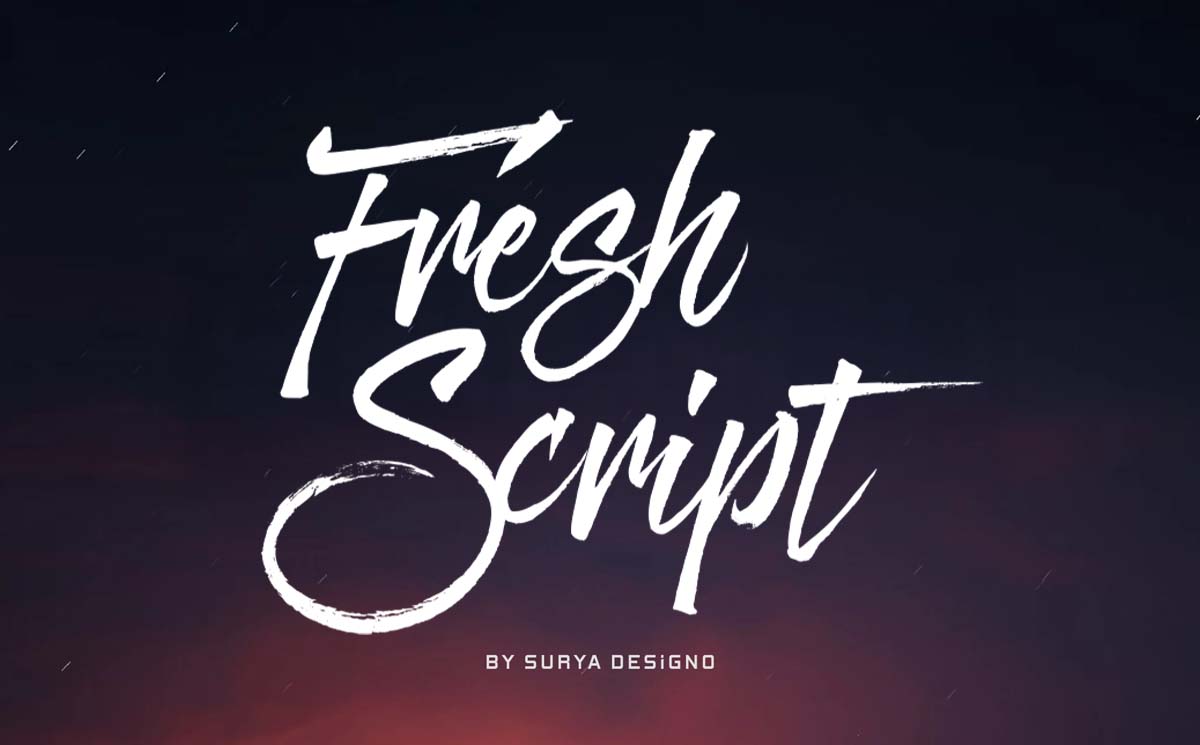
Font chữ tiếng Việt brush miễn phí cho chủ đề halloween SVN Fresh Script
SVN Fresh Script là font chữ tiếng Việt brush miễn phí sở hữu những đường nét phóng khoáng, tự nhiên và giàu cảm xúc, đặc biệt phù hợp với các thiết kế mang chủ đề Halloween. Với phong cách chữ viết tay mạnh mẽ, có chút ma mị nhưng vẫn dễ đọc, font giúp tiêu đề, poster, banner và ấn phẩm truyền thông trở nên nổi bật hơn mà không cần xử lý typography quá phức tạp.
Nếu bạn đang tìm kiếm một font brush Việt hóa để sáng tạo thiệp mời lễ hội, bài đăng mạng xã hội, hình ảnh quảng cáo hoặc nội dung trang trí Halloween, SVN Fresh Script là lựa chọn đáng cân nhắc. Bộ font mang đến cảm giác thủ công độc đáo, hỗ trợ trình bày nội dung tiếng Việt thuận tiện và có thể ứng dụng linh hoạt cho nhiều phong cách thiết kế khác nhau.
Font chữ tiếng Việt brush miễn phí cho chủ đề Halloween SVN Fresh Script đầy cá tính và ma mị
Font chữ tiếng Việt brush miễn phí cho chủ đề Halloween SVN Fresh Script gây ấn tượng nhờ kiểu dáng mô phỏng những nét cọ được viết nhanh bằng tay. Các ký tự có độ nghiêng và sự chuyển động rõ rệt, tạo cảm giác như từng con chữ vừa được vẽ trực tiếp trên bề mặt thiết kế. Đặc điểm này giúp font phù hợp với không khí sôi động, bí ẩn và có phần tinh nghịch của mùa lễ hội Halloween.
Không chỉ dành riêng cho những thiết kế kinh dị, SVN Fresh Script còn có thể được sử dụng trong nhiều dự án cần sự trẻ trung, tự do hoặc giàu năng lượng. Nhà thiết kế có thể kết hợp font với các gam màu cam, đen, đỏ sẫm, xanh rêu hoặc trắng ngà để xây dựng nhiều sắc thái khác nhau, từ vui nhộn, đáng yêu đến huyền bí và kịch tính.
Hỗ trợ tiếng Việt, thuận tiện khi trình bày nội dung
Một trong những ưu điểm quan trọng của SVN Fresh Script là khả năng đáp ứng nhu cầu thiết kế nội dung tiếng Việt. Các dấu thanh và ký tự đặc trưng giúp người dùng trình bày tiêu đề, câu khẩu hiệu, lời mời hoặc thông điệp quảng cáo bằng tiếng Việt một cách đầy đủ. Đây là yếu tố cần thiết đối với các dự án truyền thông hướng đến khách hàng trong nước, nơi tính chính xác của câu chữ ảnh hưởng trực tiếp đến chất lượng và mức độ chuyên nghiệp của ấn phẩm.
Nhờ hỗ trợ tiếng Việt, font có thể được ứng dụng cho nhiều nội dung quen thuộc như “Đêm hội Halloween”, “Lễ hội hóa trang”, “Ưu đãi ma quái”, “Bữa tiệc bí ẩn” hoặc “Kẹo hay bị ghẹo”. Người dùng không phải thay thế các từ có dấu bằng nội dung không dấu, qua đó giữ được thông điệp tự nhiên, rõ nghĩa và thân thiện với người đọc.
Phong cách brush viết tay mạnh mẽ, tạo điểm nhấn thị giác
SVN Fresh Script mang tinh thần của một font brush hiện đại với những nét chữ có độ tương phản, chuyển động và nhịp điệu linh hoạt. Kiểu chữ này tạo cảm giác gần gũi hơn so với các font hình học cứng nhắc, đồng thời giúp thiết kế có dấu ấn cá nhân rõ ràng. Khi được sử dụng ở kích thước lớn, từng nét cọ trở thành một yếu tố trang trí, góp phần tăng chiều sâu và sức hút cho bố cục.
Font đặc biệt hiệu quả khi dùng cho những thành phần cần được chú ý ngay từ lần nhìn đầu tiên, bao gồm:
• Tiêu đề poster, banner và backdrop sự kiện Halloween.
• Tên chương trình hóa trang, lễ hội âm nhạc hoặc tiệc theo chủ đề.
• Câu khẩu hiệu ngắn trên bài đăng Facebook, Instagram và TikTok.
• Thiệp mời, voucher, menu, bảng giá và tài liệu quảng cáo theo mùa.
• Tên sản phẩm, nhãn dán hoặc thiết kế bao bì phiên bản Halloween.
Để bảo đảm khả năng đọc, SVN Fresh Script nên được ưu tiên cho tiêu đề, cụm từ ngắn hoặc các nội dung cần nhấn mạnh. Với những đoạn văn dài, bạn có thể phối hợp font cùng một kiểu chữ không chân đơn giản để tạo sự cân bằng giữa cá tính và tính rõ ràng.
Phù hợp với nhiều concept Halloween từ vui nhộn đến kinh dị
Halloween không chỉ có một phong cách duy nhất. Một số thiết kế hướng đến sự đáng yêu với bí ngô, kẹo ngọt và nhân vật hoạt hình; trong khi những thiết kế khác lại khai thác lâu đài cổ, nghĩa trang, bóng ma hoặc không khí điện ảnh kinh dị. Nhờ đường nét giàu biểu cảm, SVN Fresh Script có thể thích nghi với nhiều concept nếu được kết hợp đúng màu sắc, hình khối và hiệu ứng.
Đối với phong cách Halloween vui nhộn, bạn có thể sử dụng chữ màu cam, vàng hoặc xanh lá trên nền tím than, sau đó bổ sung viền sáng để tăng độ nổi bật. Với concept bí ẩn, chữ trắng xám hoặc đỏ sẫm trên nền đen sẽ tạo cảm giác mạnh hơn. Các hiệu ứng đổ bóng, texture giấy cũ, vết mực, sương mờ hoặc ánh sáng tương phản cũng giúp nét brush của font trở nên ấn tượng mà vẫn giữ được đặc trưng ban đầu.
Dễ kết hợp font và ứng dụng trên nhiều ấn phẩm
SVN Fresh Script có thể đóng vai trò là font chủ đạo trong hệ thống nhận diện của một chiến dịch Halloween. Để bố cục không trở nên rối mắt, người thiết kế nên kết hợp font brush với một font phụ có cấu trúc gọn gàng. Font không chân phù hợp với thông tin thời gian, địa điểm, giá vé và nội dung mô tả; trong khi font có chân cổ điển có thể giúp concept trở nên huyền bí, sang trọng hơn.